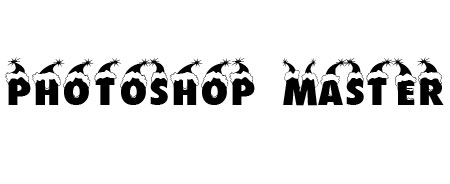
Дополнения Шрифты Татьяна Гапонова 26 июля 2009 Шрифт - Bonnet Интересный шрифт с буквами в рождественнских колпаках, без поддержки русского языка. Скачать Шрифт - Bonnet
Великолепный Шрифт
сразу вспомнилась песня "Happy New Year"
Кул
супер ))))
мне кажется много шапок)
Классно! =)
Прекрасный шрифт)
класс)